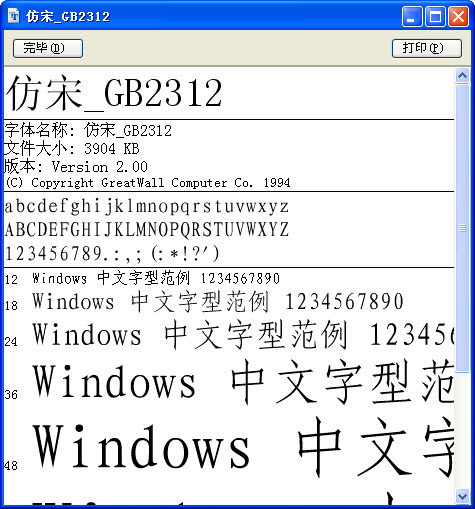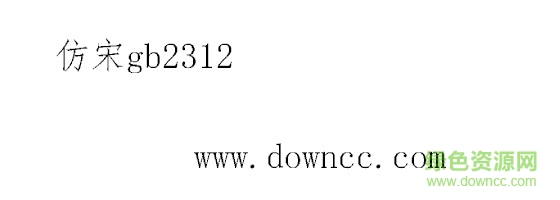
仿宋_gb2312字體是一款印刷字體,字形均勻,非常美觀,正如它的名字一樣,是仿照宋體制作的。先說明下,win7系統(tǒng)中是沒有這款字體,想要使用必須單獨安裝,win10、xp系統(tǒng)是都可以直接使用的,如果沒有的話也可以自己裝下。
1.仿宋_GB2312字體是印刷字體的一種,適用于各類打印、印刷工作
3.筆畫粗細均勻,有長、方、扁三體
仿宋gb2312與仿宋區(qū)別?
都是宋體,字型有一點不同。仿宋是一個大類,仿宋GB--2312是其中的一類。
仿宋是字體名稱,而GB2312是字符編碼名稱,它是簡體中文編碼的一種,簡體中文自1980年代以來通常使用中華人民共和國國家標準總局公布的GB 2312,以及其后繼的GBK和GB 18030中文編碼。所以通常說的仿宋就基本上是仿宋_GB2312了。
仿宋和宋體的區(qū)別是什么?